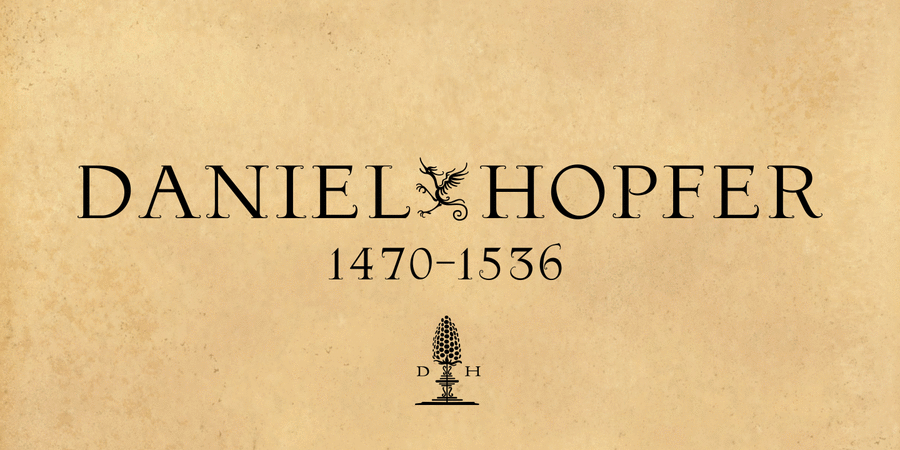
Шрифт Hopferian разработан на основе гравюр немецкого художника Даниэля Хопфера (1470-1536). При создании шрифта авторы старались сохранить архаику и некоторое несовершенство присущее прототипу, чтобы подчеркнуть его характерный шарм. Причудливые завитки на засечках придают шрифту сказочности и игривости. Гарнитура включает начертания с точками, как в оригинале Хопфера. Цифровая версия шрифта разработана Лукьяном Турецким, Марией Сокол в студии 2D Typo в 2013 году.
Асоціації з сімейством шрифтів HopferianОсобистість і характер гарнітури:
лицарський, старовинний, історичний, весільний, казковий, чарівний, химерний, вишуканий, вигадливий, потішний, майстерний, художній, благородний, ювелірний, грайливий, героїчний, витончений, красивий, виразний, характерний, епічний, дзвінкий, легендарний, прекрасний, монументальний, середньовічний, ажурний, святковий, музичний, колоритний, наївний, смачний, мотивуючий, гуманітарний, романтичний, динамічний, творчий, пивний, гарячий, вогняний, фантастичний, крафтовий, артізанальний, біблійний, християнський, церковний, релігійний, сакральний, тонкий, делікатний, легкий, пафосний
лицар, обладунки, сувій, музей, гравюра, мініатюра, весілля, мистецтво, історія, одяг, театр, казка, тату, татуювання, чарівник, король, королева, фея, дракон, фентезі, кузня, ремесло, прикраса, ювелір, дитяча книжка, кафе, десерт, геральдика, музика, магія, Чарівна казка, антикваріат, пиво, таверна, булочна, кохання, вино, свято, романтика, пам'ятник, меморіал, сукня, Christmas, кухня, паб, живопис, Трофей, нагорода, замок, сир, легенда, Біблія, графіка, ілюстрація, АСМР Гарнітура має ознаки стилів: